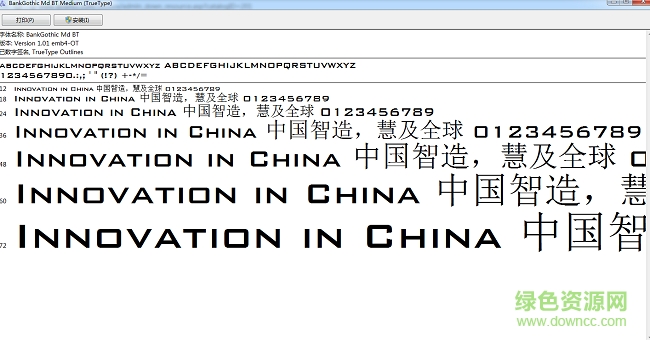
bankgothic md bt medium
bank gothic medium bt字體是一款全是由英文大寫(xiě)字母構(gòu)成的字體,結(jié)構(gòu)新穎,風(fēng)格獨(dú)特,效果非常炫,很多好萊塢大片都是使用這款字體制作電影字幕的,需要的朋友快來(lái)下載吧!
bank gothic字體介紹
Bank Gothic是一種直線型和幾何模型結(jié)合的字體,由Morris Fuller Benton于1930年設(shè)計(jì)。Bank Gothic主要有細(xì)型Bank Gothic light 和粗體Bank Gothic medium兩組構(gòu)成。